Dalam menciptakan desain logo yang keren dan menarik, penting untuk berani memilih gaya font unik agar logo tampak keren. Font salah satu elemen visual yang penting untuk membuat logo tampil keren terutama jika menggunakan teks nama merek atau inisial. Ada banyak font yang keren dengan gaya unik, untuk digunakan dalam desain logo berbagai jenis brand yang berbeda.
Desain logo perlu memiliki font yang relevan dengan brand tetapi juga tampil keren agar logo mudah dikenal dan diingat oleh audiens. Dalam desain logo cara menciptakan tampilan yang keren adalah memilih gaya font yang relevan dengan jenis brand dan bentuknya yang unik. Gaya font juga memengaruhi mood dan makna yang disampaikan dalam desain logo.
REKOMENDASI FONT KEREN UNTUK LOGO BRAND
Ada banyak sekali gaya font yang keren dan unik, untuk digunakan sebagai identitas merek pada desain logo. Setiap gaya font yang unik pun akan digunakan pada jenis brand yang relevan. Berikut beberapa rekomendasi font keren untuk beberapa logo brand:
Khuja
Font ini memiliki gaya serif yang bersih dan modern tetapi memiliki huruf yang tebal dan agak unik. Gaya huruf yang meski memiliki serif kecil yang lancip, tidak mengurangi keterbacaan teks. Pada font Khuja tersebut, penggunaan gaya hurufnya cukup unik karena tidak selalu konsisten tebal dan konsisten.
Beberapa hurufnya yang memiliki bentuk unik, membuat font tersebut tampil lebih keren dan cocok untuk gaya logo modern. Gaya huruf tersebut terlihat modern dan elegan sehingga akan cocok digunakan pada logo fashion. Font Khuja bisa menjadi pilihan menarik bagi brand yang ingin tampil elegan dan mewah.
Makota
Untuk gaya font ini memiliki jenis font sans serif yang bersih, sederhana dan bergaya modern, memiliki garis-garis elegan yang bersih sehingga juga mudah dibaca. Font sans serif satu ini tampil keren dan tidak sekaku font geometris karena garis hurufnya lebih elegan dan tidak terlalu tebal. Huruf dalam jenis font ini tampak lebih elegan dan modern sehingga cocok untuk mencerminkan brand era modern.
Gaya font Makota ini akan cocok digunakan untuk kebutuhan desain logo fashion dan kecantikan. Logo dengan font keren ini akan menciptakan kesan brand yang mewah dan high-end. Pada jenis brand fashion akan efektif mencerminkan jenis brand yang elegan dan keren.
Maori
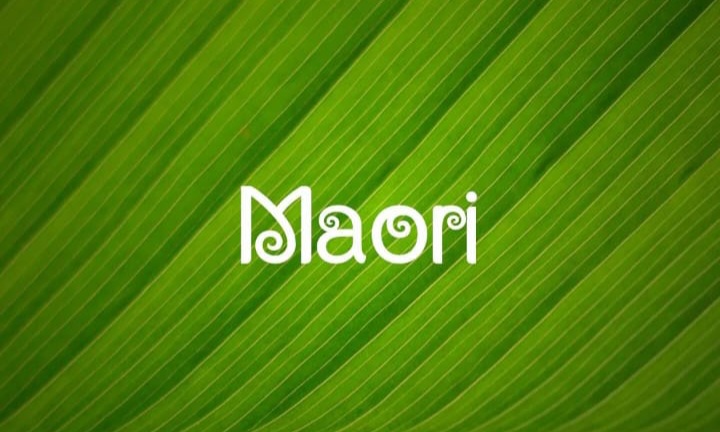
Tampilan yang keren dapat diciptakan menggunakan font yang unik seperti font maori. Penggunaan font maori yang unik tersebut akan cocok digunakan kebutuhan logo unik untuk brand alami atau bakery. Bentuk font ini cukup unik karena memiliki huruf yang melengkung pada ujung hurufnya.
Gaya melengkung yang unik tersebut dapat digunakan untuk menciptakan kesan tradisional. Bentuk huruf terlihat lebih alami sehingga juga akan cocok digunakan untuk mencerminkan brand organik. Gaya font maori ini juga akan efektif untuk membuat logo tampak keren dan berbeda dengan brand lain.
Scorn
Gaya font unik cenderung dipilih untuk membuat brand tampil lebih unik sehingga mudah diingat dan dikenali oleh audiens. Bentuk huruf dalam font ini cukup unik karena tidak memiliki garis lurus yang rata dan huruf yang tidak selalu menyatu. Gaya yang unik pada font tersebut akan membuat logo beneran unik dan beda dari yang lain.
Font scorn yang unik tersebut memiliki gaya elegan dan modern sehingga juga cocok untuk brand fashion. Untuk kebutuhan brand fashion pada jenis produk tas, sepatu hingga pakaian yang akan tampil stylish dengan font tersebut. Meski bentuk huruf cukup unik tetapi masih memiliki keterbacaan yang baik sehingga cocok untuk menciptakan desain logo yang keren.
Vinery
Font unik untuk kebutuhan brand kecantikan seperti pada logo skincare dan kosmetik bisa menggunakan gaya font vinery yang elegan. Gaya huruf dalam font ini juga bersih seperti font sans serif sehingga memiliki keterbacaan yang baik. Gunakan font seperti vinery yang meskipun bersih tetapi memiliki bentuk garis yang unik karena tidak kaku.
Huruf tersebut memiliki garis yang elegan dan tidak kaku, sehingga jenis font ini lebih cocok untuk logo brand kecantikan daripada font perusahaan yang kaku. Garis font yang halus dan elegan, akan efektif mencerminkan brand skincare yang profesional dan terpercaya. Gaya font tetap tampil unik meski hanya sederhana dan fokus pada garis hurufnya saja.
Onthel
Gaya font ini cukup meski memiliki gaya huruf yang jelas, bentuk huruf tampak bergelmbang dengan konsisten dan rapi. Gelombang pada huruf membuat font tampak lebih menarik dan membuat teks lebih unik. Desain logo dengan menggunakan font onthel akan memiliki bentuk unik dan memiliki keterbacaan yang baik.
Dalam huruf tersebut, ujung hurufnya ada yang melengkung dan lancip, menciptakan tampilan yang modern dan unik. Penggunaan yang cocok untuk gaya font yang unik dan keren ini untuk jenis logo brand modern. Baik untuk brand fashion, teknologi, atau produk modern yang bergaya stylish lainnya.
Dalam menciptakan desain logo yang keren, pilih gaya font yang unik dan pastikan mencerminkan brand dengan baik. Keunikan sebuah font terlihat dari penggunaan serif yang panjang, bentuk huruf yang tidak lurus hingga dekorasi tertentu. Penting untuk memilih font yang keren agar desain logo unik dan tampil beda. Font akan efektif mencerminkan jenis brand dan karakter merek melalui gaya huruf yang unik.